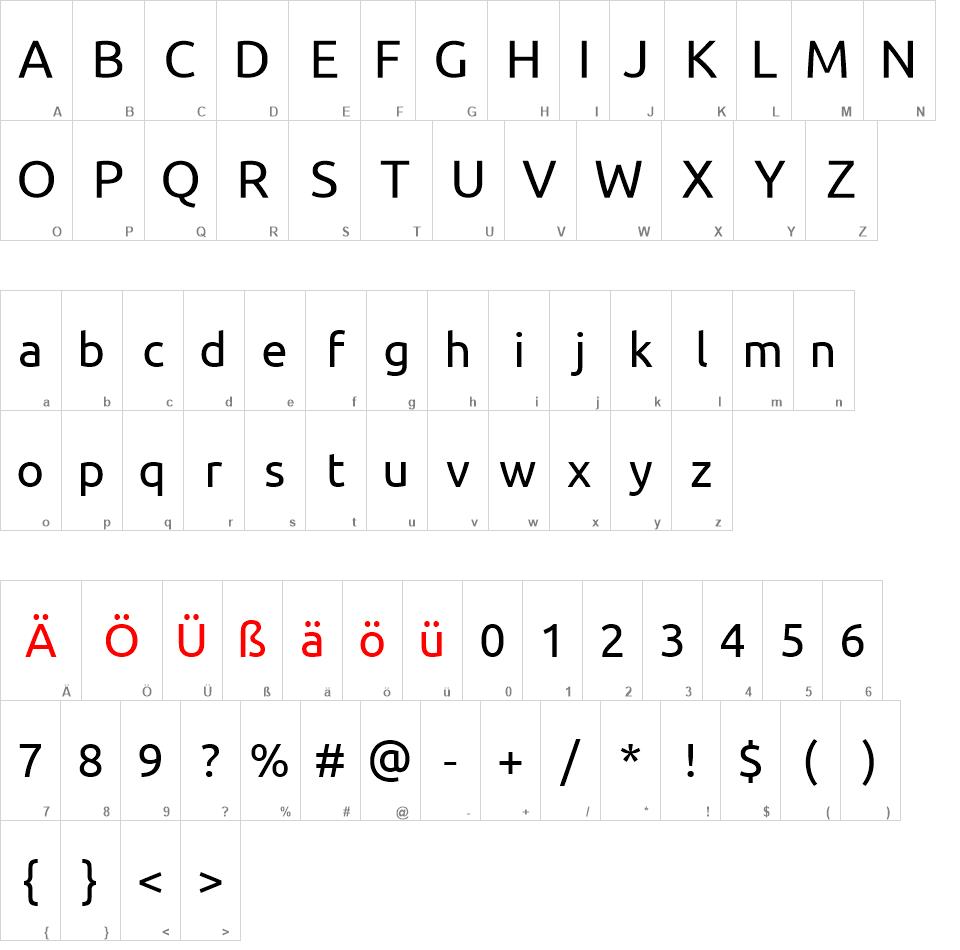
Ubuntu
Ubuntu font
Die Ubuntu Schriftfamilie besteht aus einer Reihe von Sets, die zwischen 2010-2011 neuen Libre / Open Fonts entsprechen. Im Namen der Entwicklung, Canonical Ltd. Die breite Free Software Community und wird vom Ubuntu Projekt finanziert. Technische Designstudien und -implementierungen werden von Dalton Maag durchgeführt.
Die neue Ubuntu-Schriftfamilie wurde eingeführt, um die Ubuntu-Persönlichkeit sichtbar zu machen, und alle Menüs, Schaltflächen und Kontakte wurden wahrgenommen. Die Schriftart Sans-Serif verwendet die Funktionen von OpenType und ist für die manuelle Darstellung auf Desktop- und mobilen Computerbildschirmen gedacht.
Ubuntu Schriftfamilie Abdeckung für jeden Benutzer in der Sprache ihrer Wahl sollte in der Lage sein, ihre Software zu benutzen, um die Welt darauf hinweist, dass Ubuntu-Philosophie in Einklang mit Ubuntu enthält alle von den Benutzern verwendete Sprachen. Das Ubuntu Font Family-Projekt wird daher um viele weitere geschriebene Sprachen erweitert.